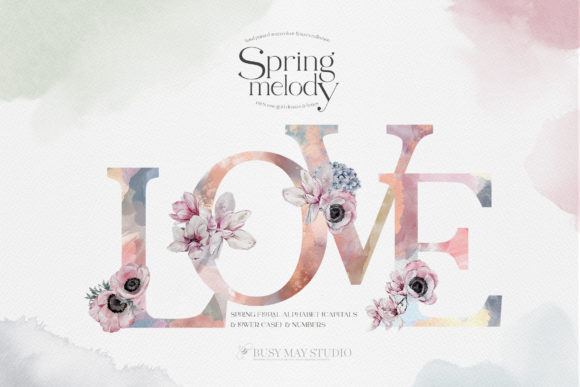
Watercolor Floral Alphabet Numbers PNG
Att hitta rätt designelement kan vara utmanande, men Watercolor Floral Alphabet Numbers PNG erbjuder en exceptionell samling som omedelbart lyfter ditt arbete.
Tillverkad med precision, ger Watercolor Floral Alphabet Numbers PNG rena vektorer, smidig typografi och en kommersiell licens för sinnesfrid.
Oavsett om du skapar POD-produkter (Print on Demand), bröllopsinbjudningar eller grafik för sociala medier, är Watercolor Floral Alphabet Numbers PNG ett perfekt val.